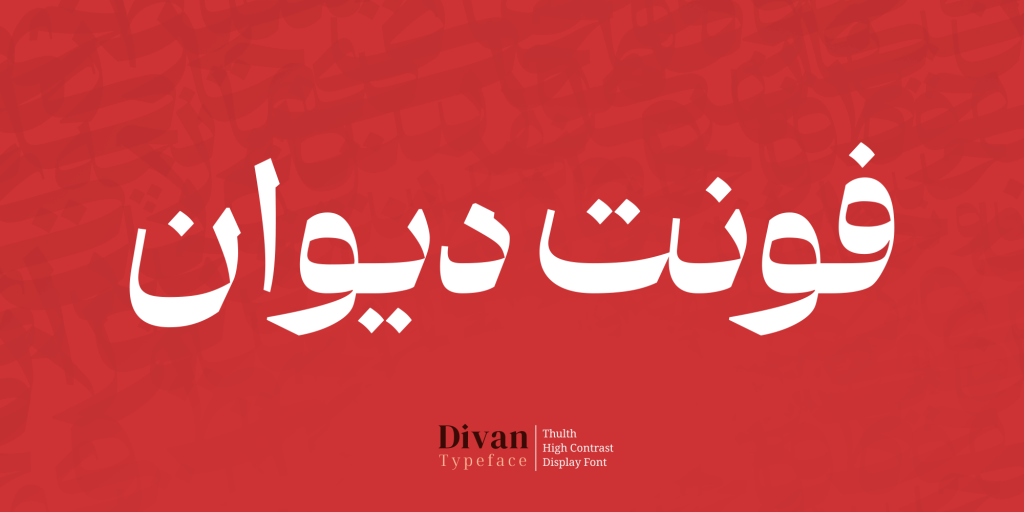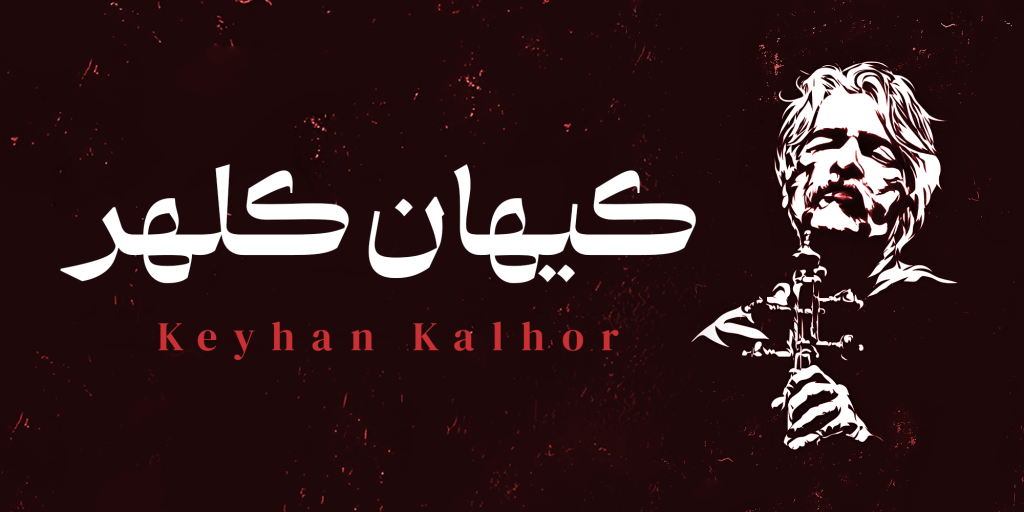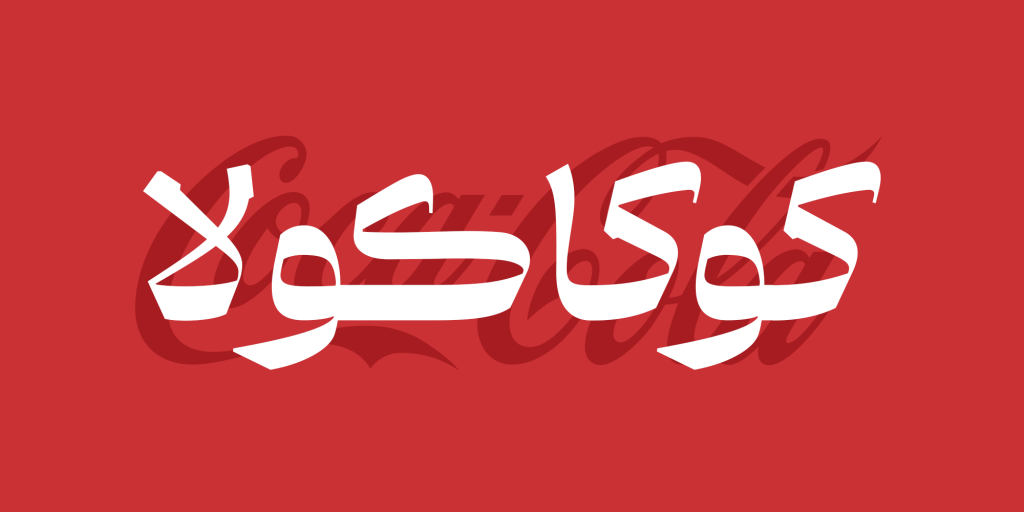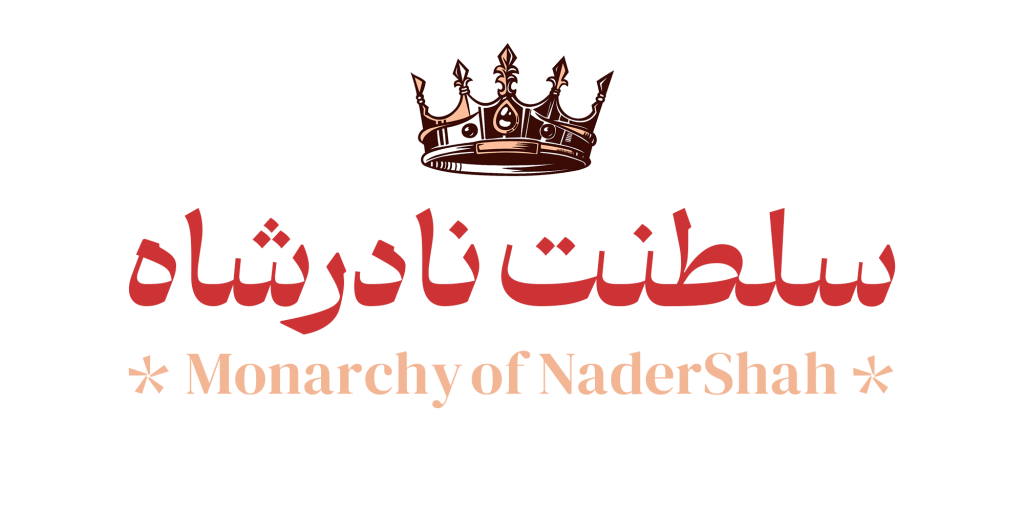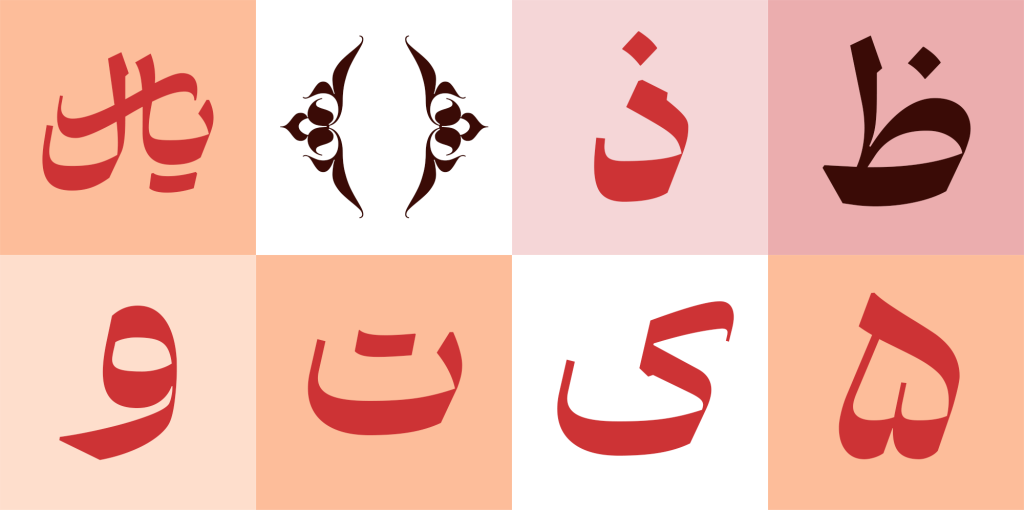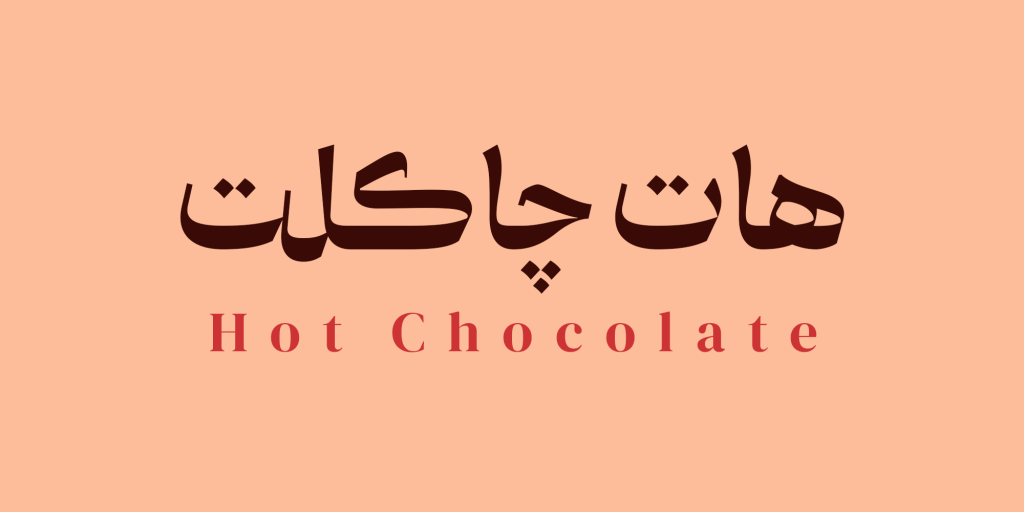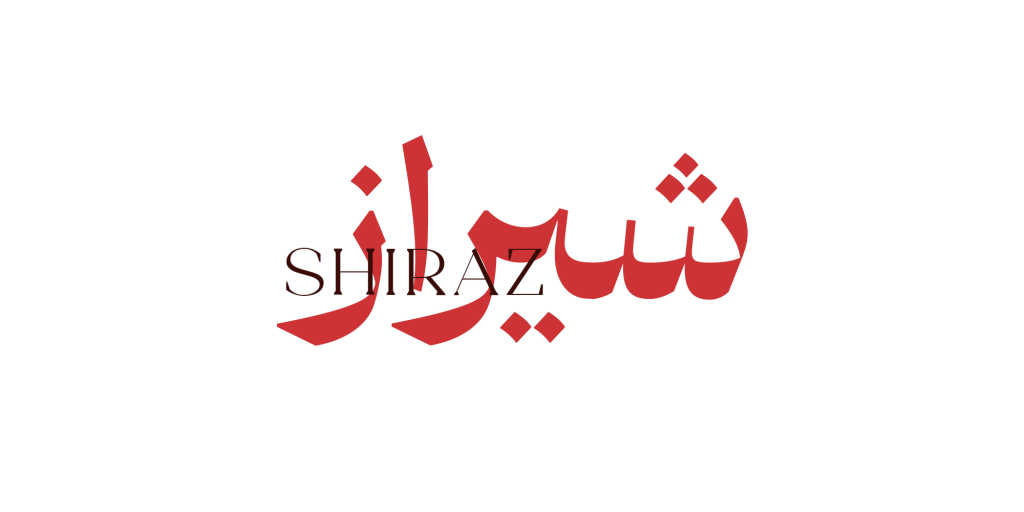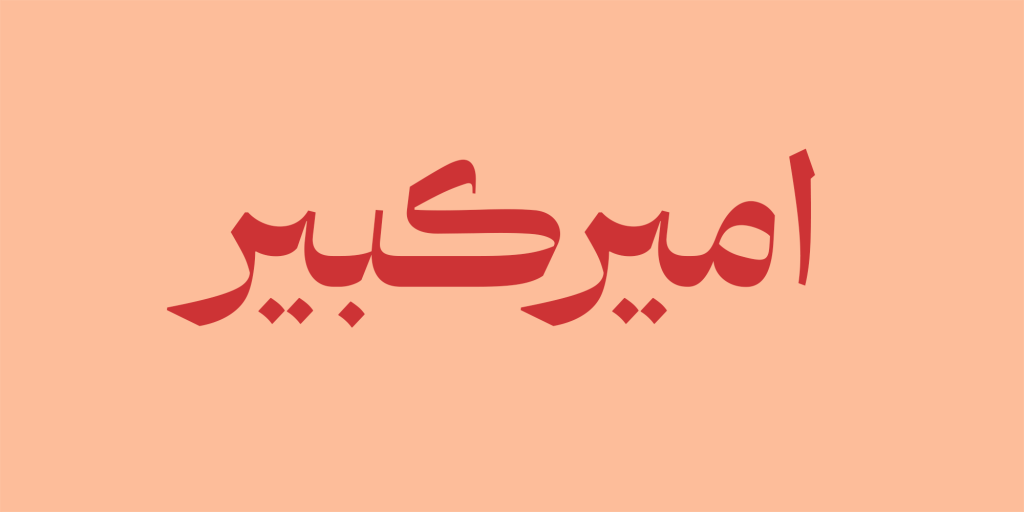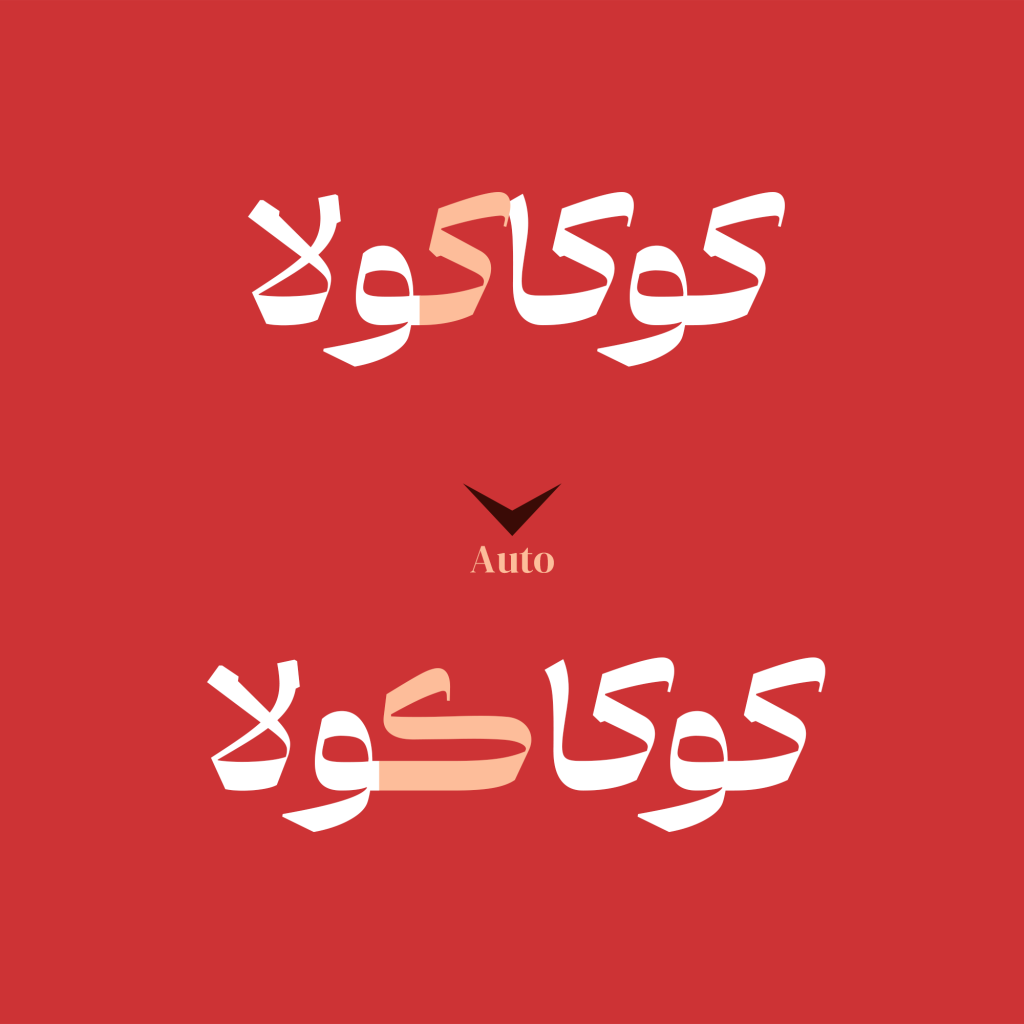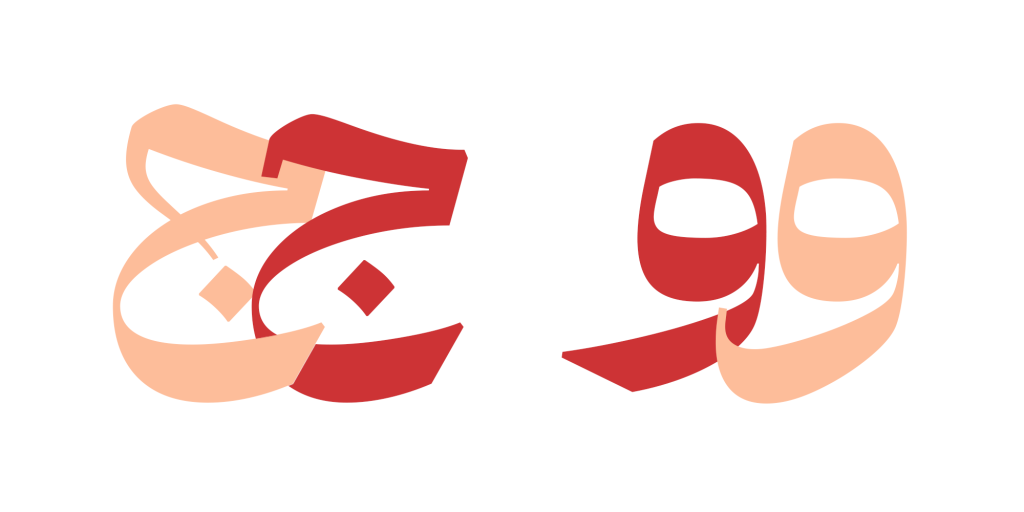
فونت دیوان – آمیخته ای از هنر خوشنویسی
دیوان فونتی اصیل و نجیب که آمیخته ای از دو خط خوشنویسی ثلث و نسخ است. این قلم ماحصل گذشته و آینده است. دارای کنتراستی بالا در سطح می باشد. همچنین دارای ویژگی نمایشی است تا نگاه خوانندگان را به خود جذب کند با وثار است و دارای روحیه ای قاطع است در عین حال که متین و منعطف نیز است.
شما عزیزان می توانید درانواع پروژههای فرهنگی، هنری، ادبی و سنتی است و در طراحی تیترها، عناوین، متنهای کوتاه تبلیغاتی، پوستر، کاور، جلد کتاب و… از دیوان بهره مند شوید . در این قلم هویت خط، با نوآوری معاصر آمیخته ای را رقم زده اند تا نوشتار را به یک اثر هنری ممتاز تبدیل کنند.
پشتیبانی قلم دیوان از زبان های مختلف
تایپ فیس دیوان از زبان های بسیاری پشتیبانی می کند از جمله این زبان ها می توان به زبان های فارسی، تورکی، عربی، اردو، کوردی و جاوی و … اشاره نمود این تنوع از پشتیبانی گزینهای بیهمتا برای طراحان خوشذوق تایپوگرافی فارسی است تا توانمندی های خود را در قالب این قلم به تصویر کشند.